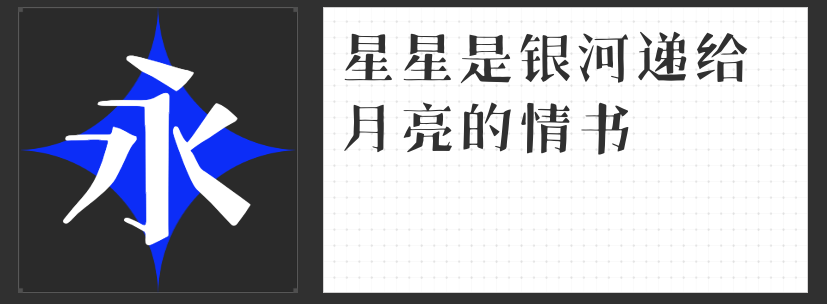
四款独具魅力的创意字体推荐➿
在字体设计的世界中,创意字体以其独特的风格和表现力,成为了设计师们手中的得力助手。今天,我们为大家推荐四款极具创意的字库字体。这些字体不仅各具特色,还能为设计作品增添独特的魅力。
首先登场的是“高手庆科帅黑体 大黑”。这款直线黑体以其硬朗倾斜的整体造型,让人眼前一亮。中宫略大、布白均匀的设计,使得字体在视觉上更加统一和谐。笔画的简约设计,横细竖粗的对比,以及笔画起笔收笔的平切处理,都使得这款字体在保持现代感的同时,又不失传统韵味。其整体倾斜约6”。度的这款设计创意,黑更是体字为以其字体粗壮增添了一份的动感。
接下来是“励字铁拳简 超级黑”笔画和宽大的字面,展现出强烈的视觉冲击力。饱满的块面感和折角圆的设计,使得字体犹如铁拳出击,横扫千军。无论是用于标题还是正文,都能瞬间吸引读者的目光。
再来看看“高手字斋东京体”。这款字体以其独特的方块字型设计,区别于古代版本的中长形字。粗体敦厚疏朗的风格,使得字体在横排、竖排时都能保持清晰的笔画和强烈的跳出性。光洁平滑的字体曲线,让人感到亲和舒畅,既古又新的字型设计,更容易让人记忆深刻。
最后是“高手庆科手绘宋”。这款手写感为基础的宋体,以其生动灵活的笔画设计,赢得了众多设计师的喜爱。保持传统宋体横细竖粗的特点,同时加入三角形装饰角和转折的长撇笔画,使得字体在传统与现代之间找到了完美的平衡点。沿袭中文设计特点的西文符号,也使得这款字体在搭配使用时更加统一和谐。
总之,这四款创意字体各有千秋,无论是用于平面设计、网页设计还是移动应用界面设计,都能为作品增添独特的魅力和视觉效果。快来试试这些字体吧,相信它们一定会成为你设计路上的得力助手!